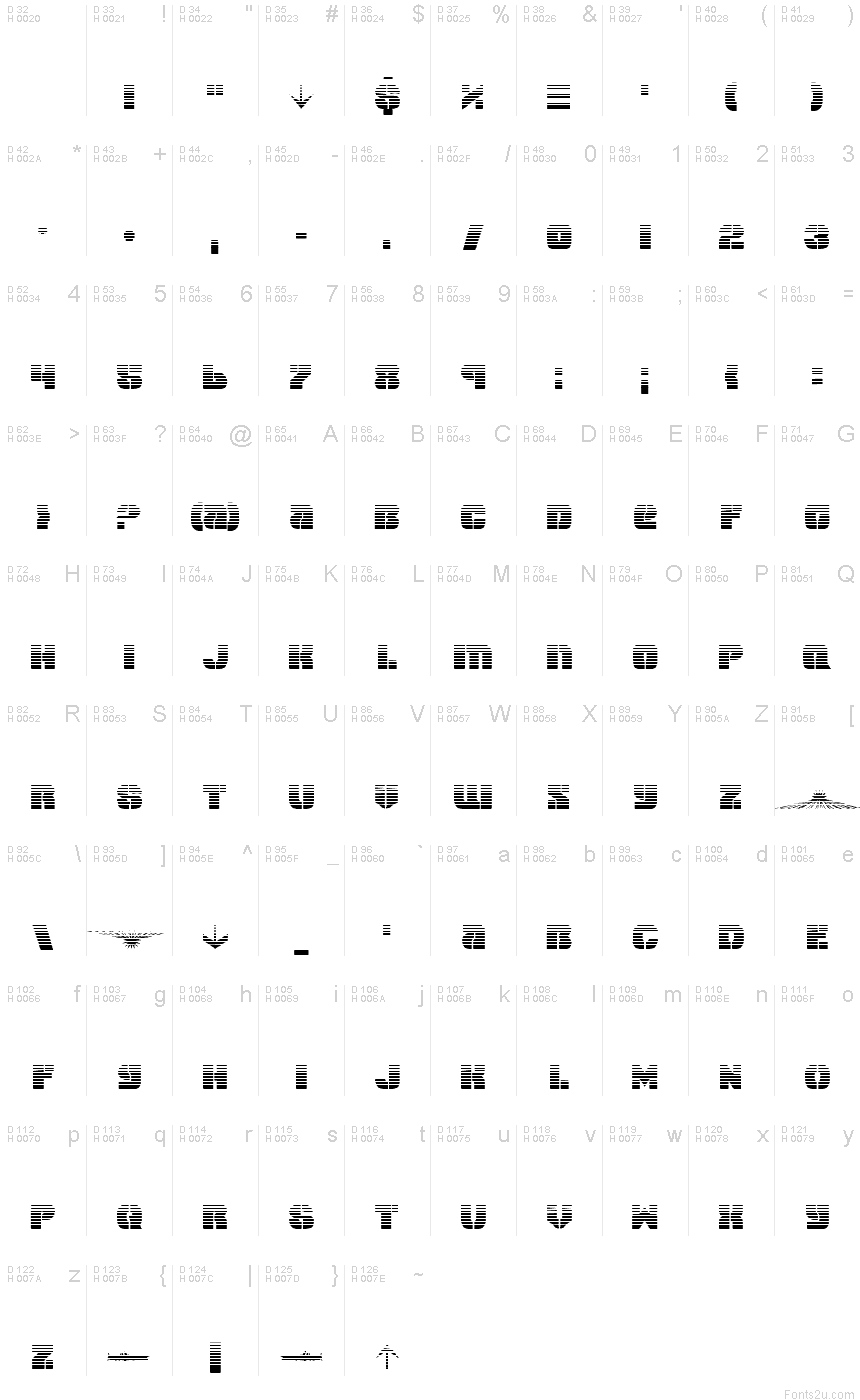
Space Cruiser Gradient
خط Space Cruiser Gradient من Iconian Fonts هو خط مجاني بتصميم تقني (Techno) وأحرف كبيرة (Caps) يتميز بلمسة خيال علمي حيوية. الحروف مبنية من خطوط أفقية متكررة تمنح الخط ملمساً متحركاً يشبه الإشارات، بينما تحافظ الزوايا المستديرة والقطع الحاد على مظهر الخط الجريء والمتماسك.
يناسب هذا الخط عناوين الملصقات، والعلامات التجارية المستوحاة من ألعاب الأركيد، وأغلفة الألبومات، وبطاقات العناوين، وقوائم الألعاب حيث تتطلب الأجواء المستقبلية إيقاعاً بصرياً أقوى مما يقدمه الخط العادي بلا زوائد. وبما أنه خط مجاني، فهو مثالي أيضاً للنصوص القصيرة والشعارات، لأن نمط الخطوط المكسورة يقوم بمعظم العمل البصري بحد ذاته.